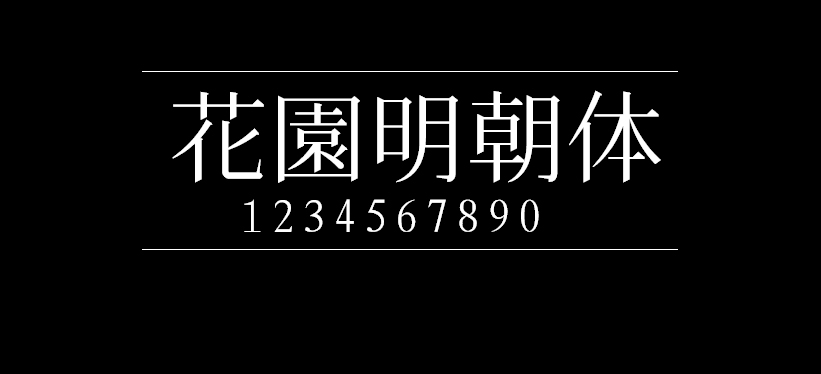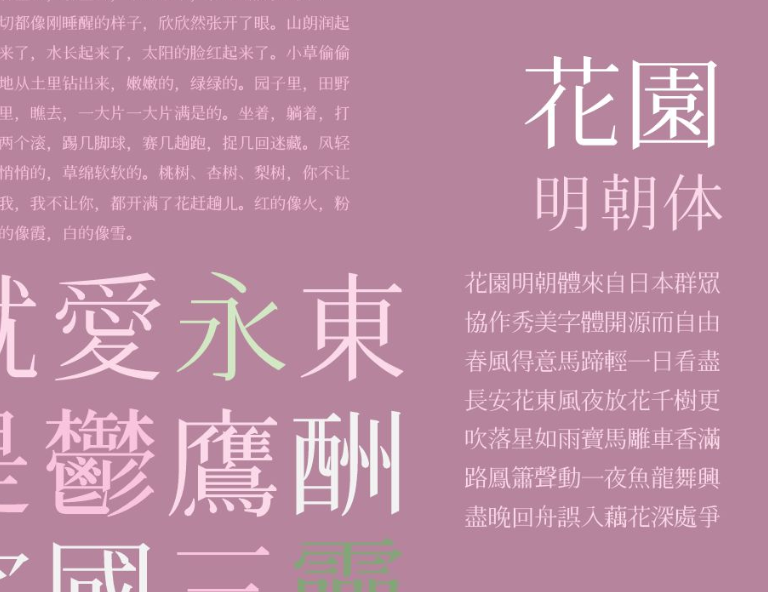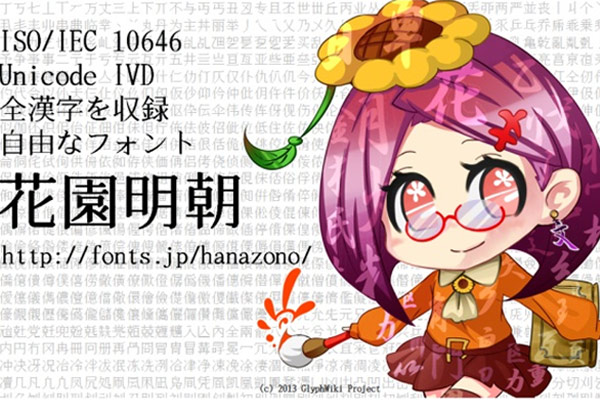
花园明朝体
日本花园明朝体在免费字体中算是非常非常好的一款了,花园明朝 (Hanazono) 是一个免费字体,为 GlyphWiki 所研发,字形数量共 45090 + 47186 个,几乎收录了所有汉字字形(但看起来没有区分不同地区标准字形)。
一共收录了八万多汉字的免费字体,本次发布的是八万汉字完整版。
第一步这个字体的轮廓是用 CHISE 计划的影系统生成的,数据来源就是 Glyphwiki,因此可以在相对短的时间内生成N多的文字(貌似今年刚补完日本的户籍统一文字),但是影系统生成的笔画轮廓实在是不敢恭维,其避让系统也不算很完善,不能用来生成很粗的字。